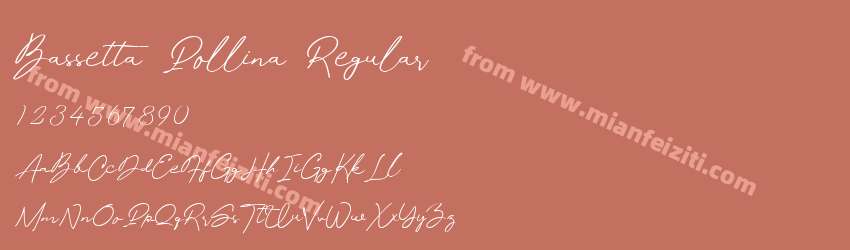
Bassetta Pollina Regular
字体名称: Bassetta Pollina Regular
Postscript名称: BassettaPollinaRegular
本款“Bassetta Pollina Regular”是一款书写很新颖的字体,字体大方,适合各种设计作品使用!欢迎下载!